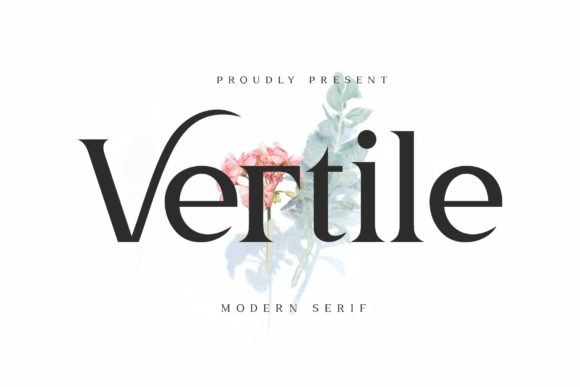
Creativefabrica Vertile Font 2021
[Creativefabrica] Vertile Font (2021)
Vertile - это элегантный и смелый шрифт с засечками.
Он характеризуется плавными изгибами и идеально подходит для модного брендинга или редакционного дизайна.